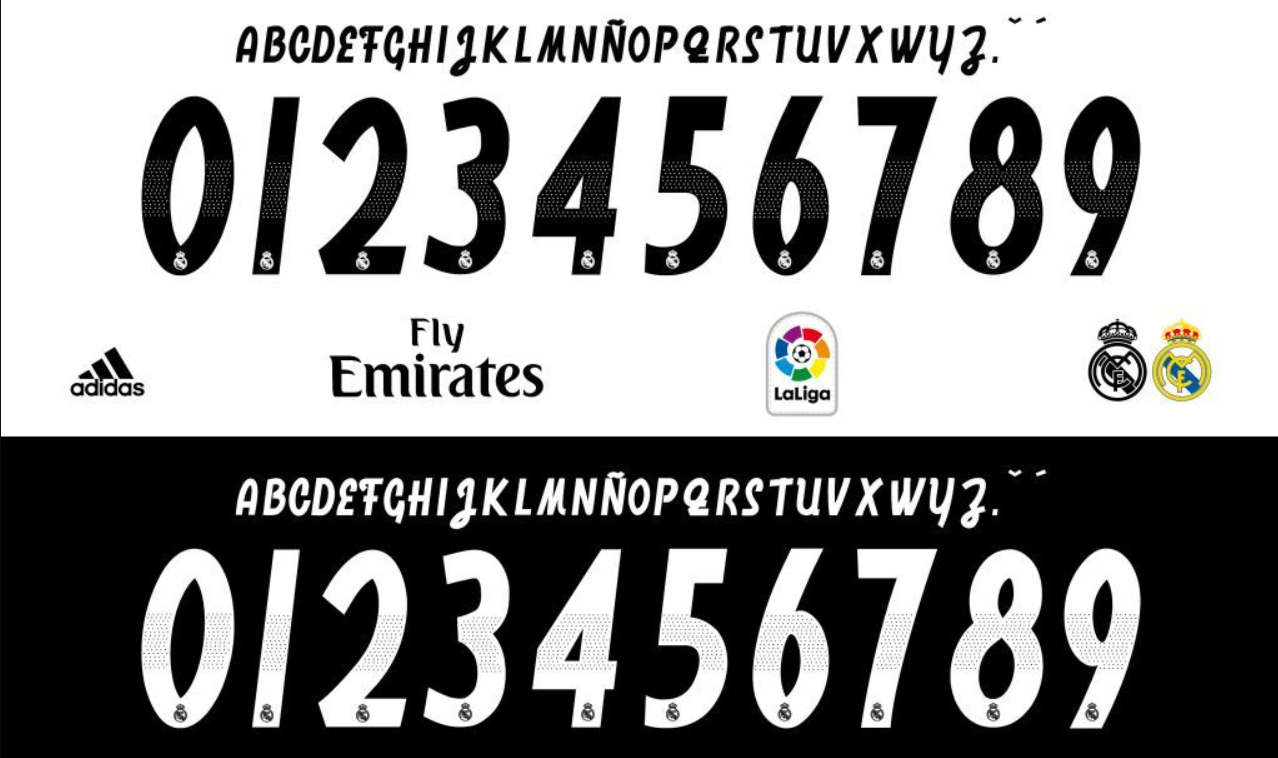
Quando falamos em realeza no futebol europeu, a camisa branca do Real Madrid é a referência máxima. Na temporada 2019/2020, a Adidas trouxe de volta a combinação icônica de branco com dourado, evocando a glória dos “Galácticos”.
Para designers, personalizadores de camisas e fãs que buscam recriar esse uniforme histórico – que vestiu lendas como Sergio Ramos, Benzema e Modric na conquista da La Liga –, disponibilizamos o arquivo exato da tipografia utilizada.
Estilo Visual e Aplicação
A fonte criada pela Adidas para o Real Madrid nesta temporada fugiu do padrão genérico. Inspirada na arquitetura moderna e nos planos de renovação do estádio Santiago Bernabéu, a tipografia apresenta um design ligeiramente “condensado” com cortes angulares únicos.
O grande destaque visual é a aplicação original em dourado, que contrasta perfeitamente com o fundo branco da camisa titular (Home Kit) e com o azul marinho do uniforme reserva (Away Kit). É uma fonte que transmite modernidade, mas sem perder a classe aristocrática exigida pelo clube merengue. Ideal para quem deseja um acabamento premium em seus produtos.